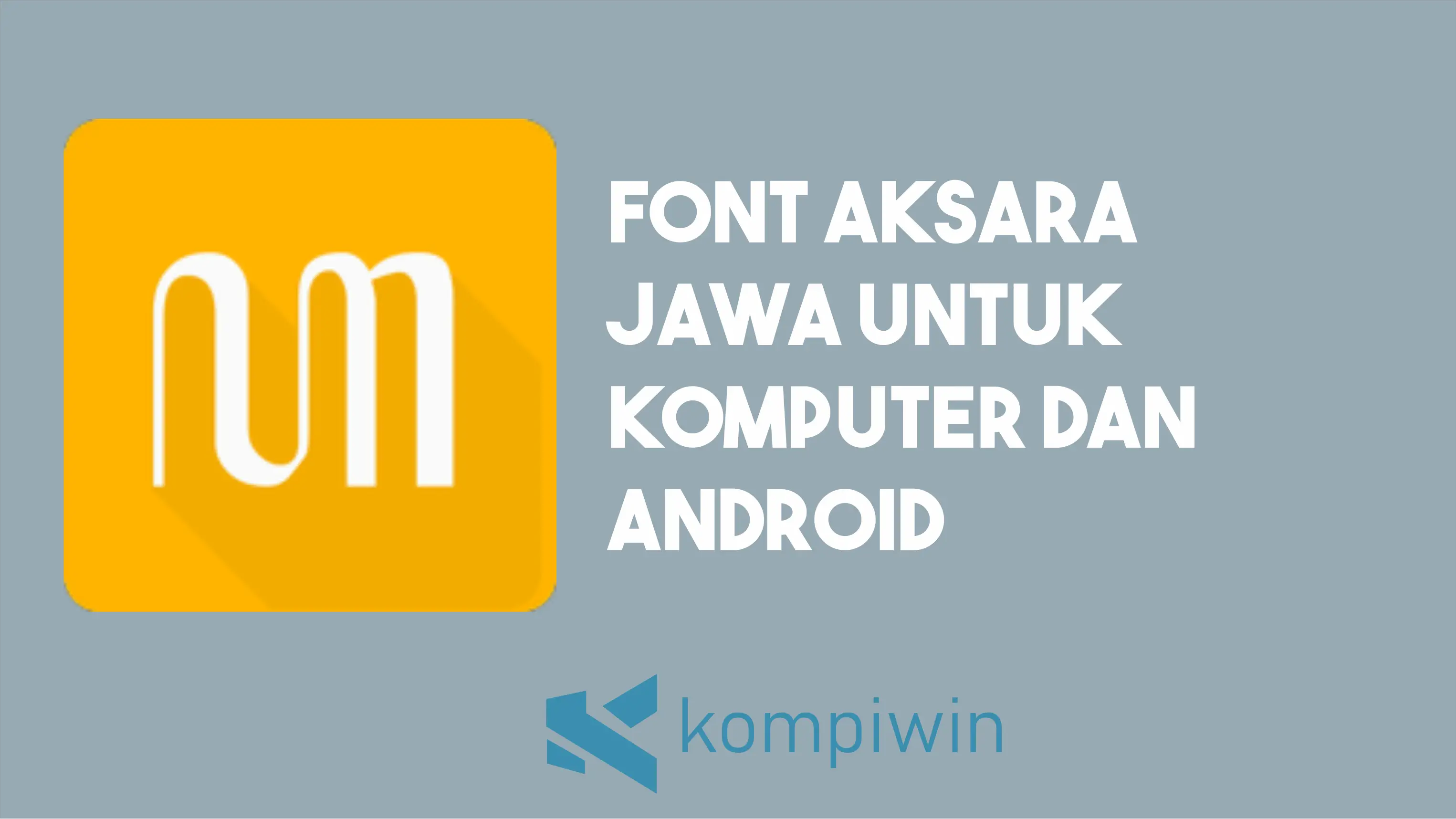
Indonesia memiliki banyak sekali ragam budaya yang berbagai macam. Salah satu warisan budaya yang harus dilestarikan adalah huruf Aksara Jawa.
Bagi orang Jawa, mengenal tulisan Jawa kuno ini tentu mudah bagi mereka. Huruf Aksara Jawa memiliki 4 baris kata antara lain sebagai berikut:
| ꦲ | ꦤ | ꦕ | ꦫ | ꦏ |
| Ha | Na | Ca | Ra | Ka |
| ꦢ | ꦠ | ꦱ | ꦮ | ꦭ |
| Da | Ta | Sa | Wa | La |
| ꦥ | ꦝ | ꦗ | ꦪ | ꦚ |
| Pa | Dha | Ja | Ya | Nya |
| ꦩ | ꦒ | ꦧ | ꦛ | ꦔ |
| Ma | Ga | Ba | Tha | Nga |
Masing-masing dari kalimat tersebut memiliki arti yang luas jika kita terjemahkan serta bersejarah panjang. Akan tetapi, kita tidak akan membahas mengenai isi dan muatan dari huruf Aksara Jawa.
Kami akan membahas mengenai font Aksara Jawa untuk komputer atau laptop dan HP Android. Font ini dapat digunakan untuk membuat dokumen dengan tulisan Aksara Jawa.
Font Aksara Jawa
Aksara Jawa sering digunakan untuk membuat sebuah karya sastra, kebutuhan pendidikan, pembuatan surat khusus, dan masih banyak lainnya.
Aksara Jawa tentu saja familiar di wilayah Jawa sendiri. Selain budaya Jawa, ada beberapa warisan aksara seperti Aksara Sunda dan juga Aksara Bali.